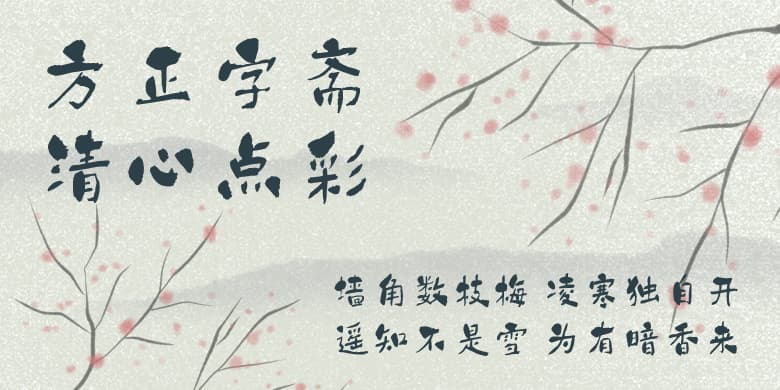
方正字斋清心点彩
品牌:方正字库设计师:刘汉旭发行时间:2021字库编码:大陆简体(GB2312-80)分类:创意书写字体属性:精品字
《方正字斋清心点彩》把趣味性理解得很透彻,风格独特。根据产品行业类别、属性、功能等,可以用恰如其分的字体来点亮产品,合适的表达自我,是字体最体面的环境呈现,这是用时间、工作量累积出来的职业素养,重点是字体的品格能带给受众的感受,无论轻松、愉快、调皮、积极、天真、可爱等等,通过字体表情达意,能感受到“无声胜有声”即“上乘之作”。